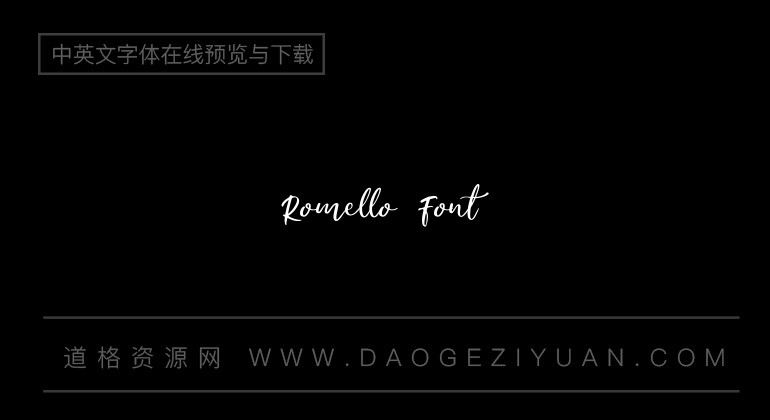
Romello Font是一种流行的手写风格字体,由设计师Nirmana Visual设计。它具有自然、流畅和美观的特点,适用于很多场合,例如印刷品、海报、徽标、包装等等。 这种字体有两种风格——常规和斜体。它的字母形状都非常独特,形态各异,有些字母的笔画很粗,有些字母的笔画则很细,这种差异性使它在设计中更具有表现力。 Romello Font的设计灵感来自于现代手写风格,字母之间的间距非常合适,使得阅读更加轻松流畅。此外,这种字体包含了大量的特殊字符和标点符号,因此在设计中非常实用。 总之,Romello Font是一种非常优秀的手写风格字体,它的独特和美观使得它在设计领域中非常受欢迎。内容介绍
Romello Font是一款非常不错的手写艺术字体,具有很好的视觉感,适合于文化类的宣传设计、商业类品牌的广告和产品包装设计以及个性化文字排版等较多场景。